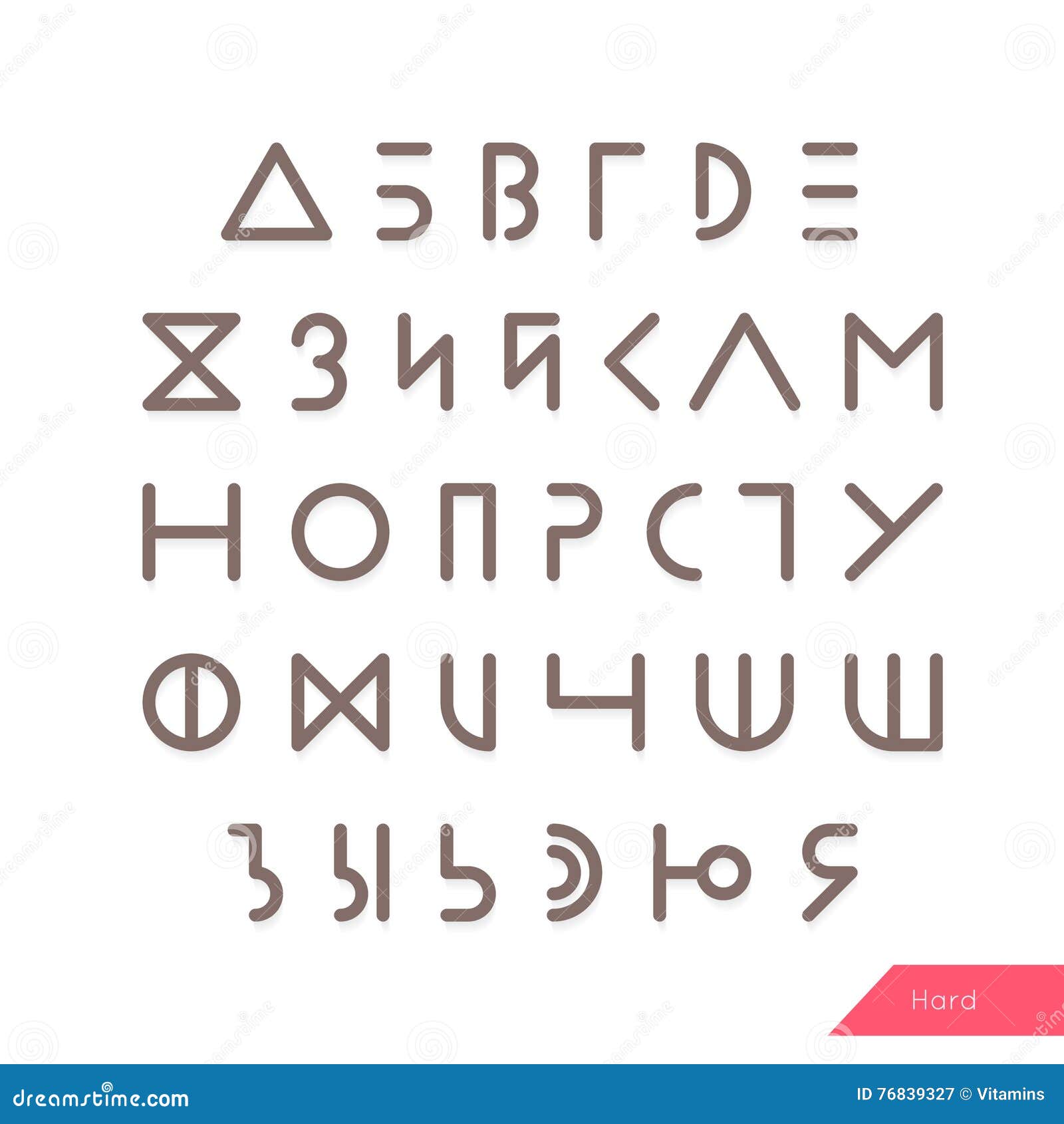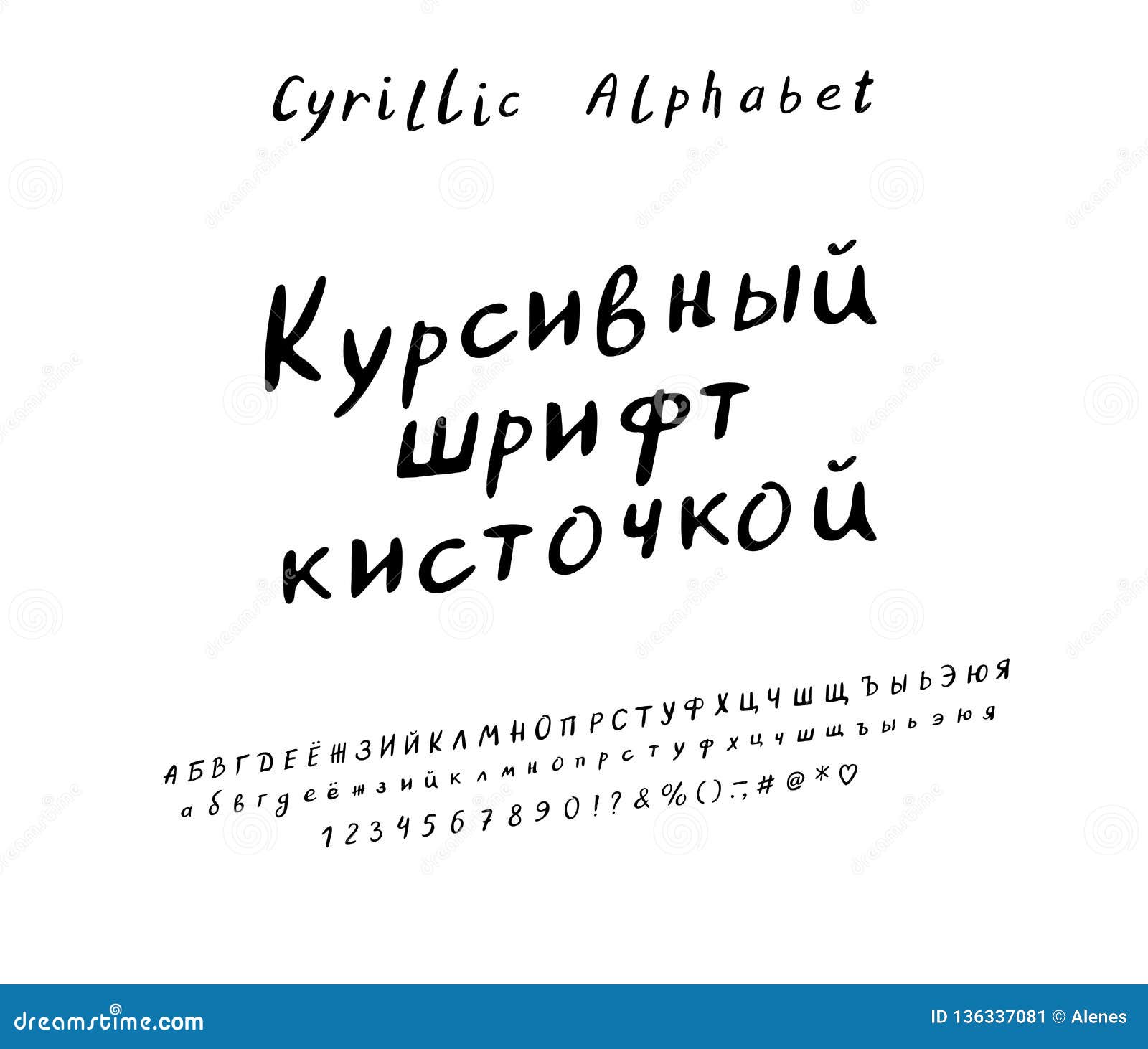
Идеальные шрифты для русского алфавита: как создать уникальный дизайн с помощью правильного выбора
Шрифты имеют огромное значение в дизайне и могут определить уникальность вашего проекта. Узнайте, как выбрать подходящие шрифты для русского алфавита и создать привлекательный дизайн.
Изучите основные типы шрифтов и их влияние на восприятие текста. Выберите шрифты, которые отражают характер вашего проекта.
Удостоверьтесь, что выбранные шрифты легко читаемы и подходят для чтения на разных устройствах и экранах.
Используйте контрастные шрифты для создания интересных и привлекательных текстовых блоков.